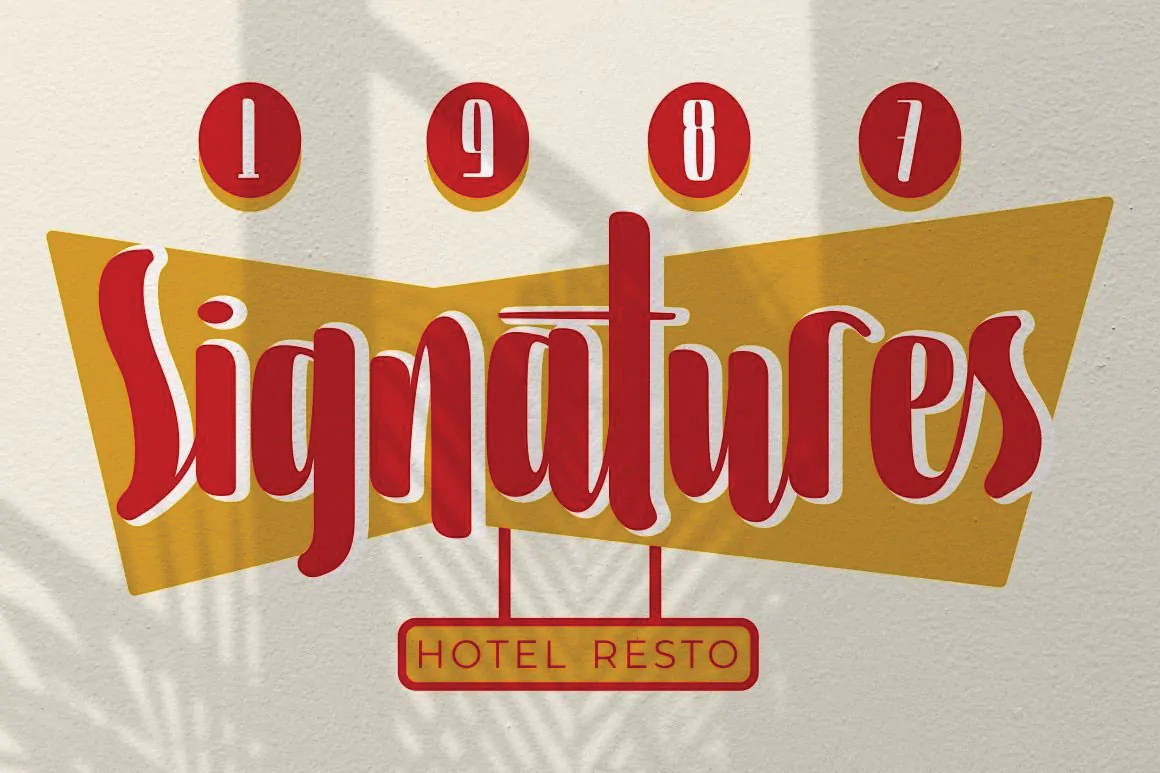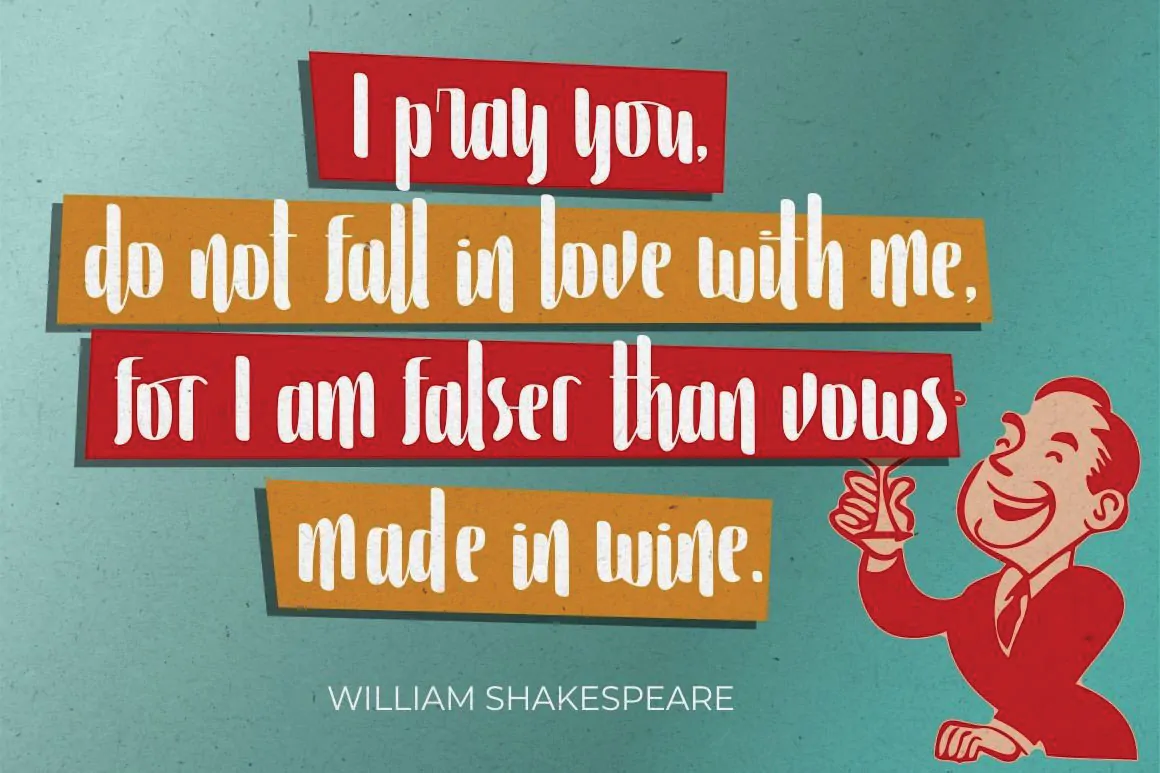
فونت کلاسیک و وینتج Violinist
فونت کلاسیک و وینتج انگلیسی
فونت کلاسیک و وینتج Violinist یک قلم انگلیسی فوق العاده زیبا است که مناسب برای استفاده در طرح و پروژههای گرافیکی مختلف میباشد. این فونت و قلم زیبا با وزن معمولی طراحی شده است که میتوان از آن در طراحی بسته بندی محصولات، ظروف کاغذی یکبار مصرف، لوازم التحریر، پوستر و … استفاده نمود.